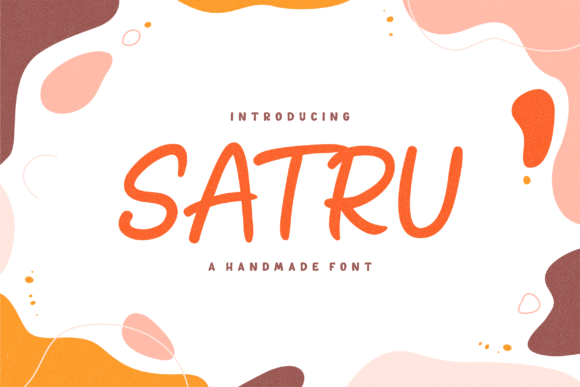
Satru a Handmade Playful Display Font
Mencari elemen desain yang tepat bisa jadi sulit, namun Satru a Handmade Playful Display Font menawarkan koleksi luar biasa yang akan langsung meningkatkan kualitas karya Anda.
Dibuat dengan presisi, Satru a Handmade Playful Display Font menyediakan vektor yang bersih, tipografi yang halus, serta lisensi komersial untuk ketenangan pikiran Anda.
Who Is This Best For?
Baik Anda membuat produk POD (Print on Demand), undangan pernikahan, atau grafis media sosial, Satru a Handmade Playful Display Font adalah pilihan yang sangat ideal.
Tips Ahli: Padukan elemen-elemen ini dengan font pendamping untuk menciptakan desain unik dan menarik yang menonjol di pasaran.